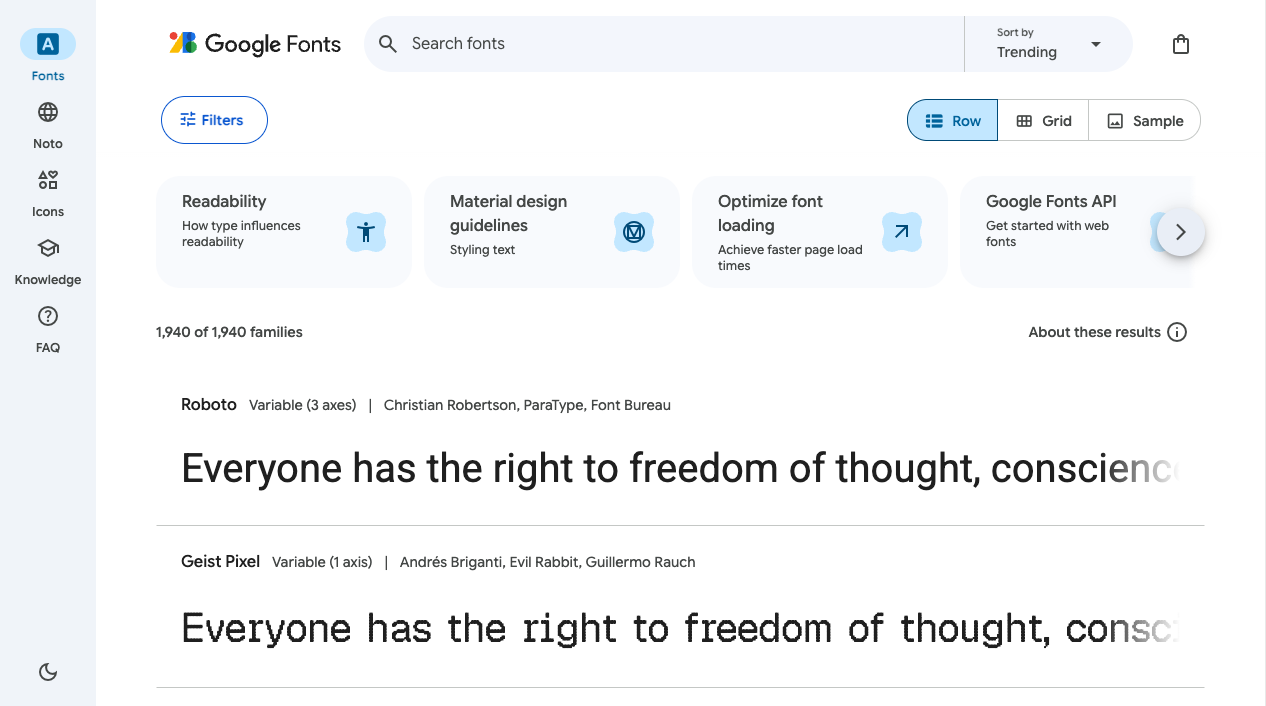
Google Fontsで文字の顔を変える
同じ文章でも、フォント(文字の形)を変えるだけで印象がガラッと変わります。無料で何百種類も使えるGoogle Fontsを、コピペ2か所でページに取り入れる手順を紹介します。
パソコンには最初からいくつかフォント(文字の形)が入っていますが、種類はそう多くありません。でもWebには、無料で使えるフォントを配ってくれる場所があります。それが Google Fonts。丸っこい文字、手書き風、かっちりした明朝体——気分に合わせて、ページの“文字の顔”を選べます。
1. フォントを選ぶ
まずはサイトを開いて、気になるフォントを探します。
Google Fontsの一覧画面。上に検索欄、下にRoboto・Geist Pixel・Yuyuなど、いろいろな形のフォントで同じ例文が表示され、文字の顔つきが1つずつちがう
同じ例文が、フォントごとにまったくちがう表情で並びます。丸っこいもの、四角いもの、手書き風——眺めているだけでも楽しいです。
日本語のフォントを探すときは、Filters から「Japanese」を選ぶと、日本語に対応したものだけが並びます。気に入ったフォントを選んだら、右上あたりの 「Get font」→「Get embed code」 に進みます。
すると、こんな感じの <link ...> のコードが出てきます(@import ではなく <link> の方を選びましょう)。これをコピーして、HTMLの <head> の中に貼りつけます。
これで、そのフォントがページに読みこまれる準備ができました。まだ見た目は変わりません。「使ってね」とCSSで指定するのが最後のステップです。
3. CSSで font-family に書く
同じページの埋め込みコードの中に、こう使ってね、という一行も書いてあります。それをCSSにうつします。
保存してブラウザを見ると——文字の形が変わっているはず。body に書けばページ全体、h1 に書けば見出しだけ、と場所も選べます。
見出しだけ好きなフォントにして、本文はふつうのまま——これだけで“作った感”が一気に出るよ。まずは1つ、お気に入りを見つけてみて〜
まとめ
1. Google Fontsは無料で使えるWebフォントの宝庫
2. <head><link> を貼って、フォントを読みこむ
3. CSSの font-family に名前を書いて、はじめて反映される